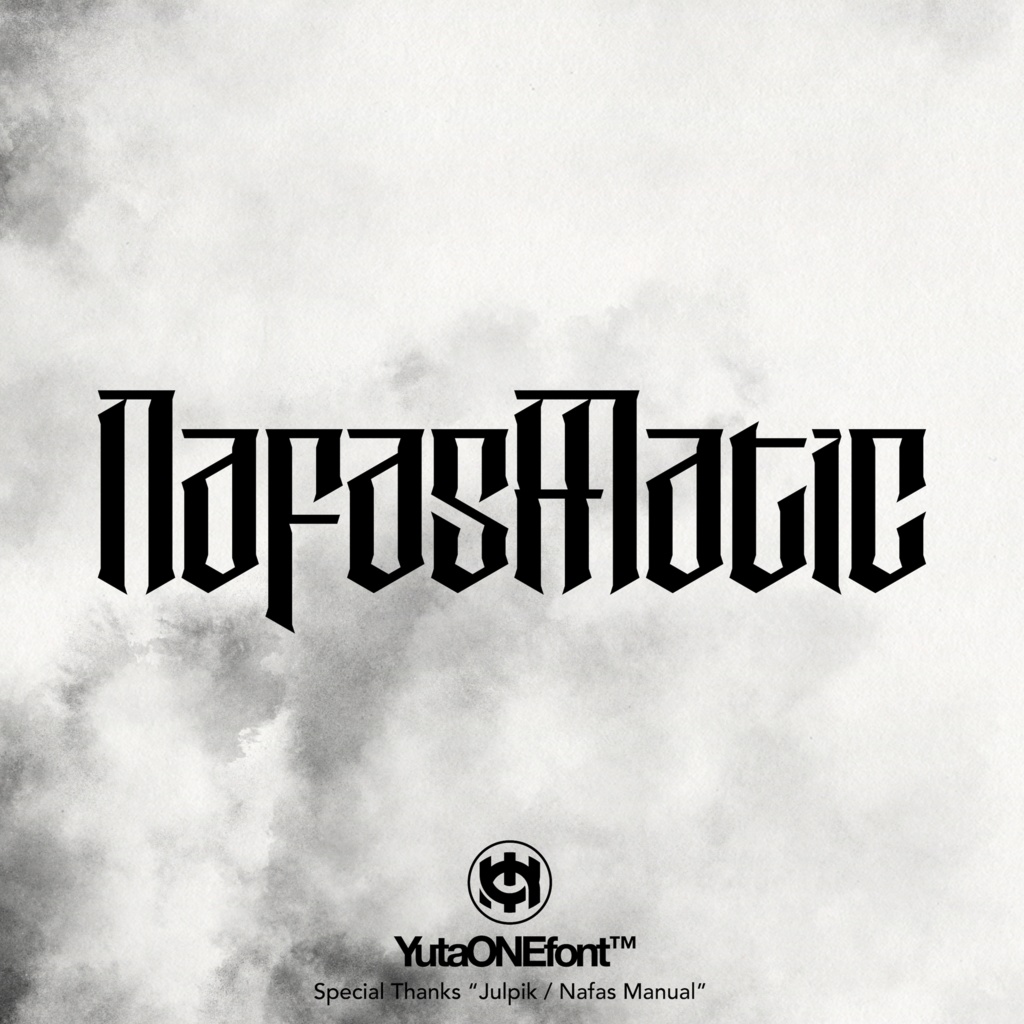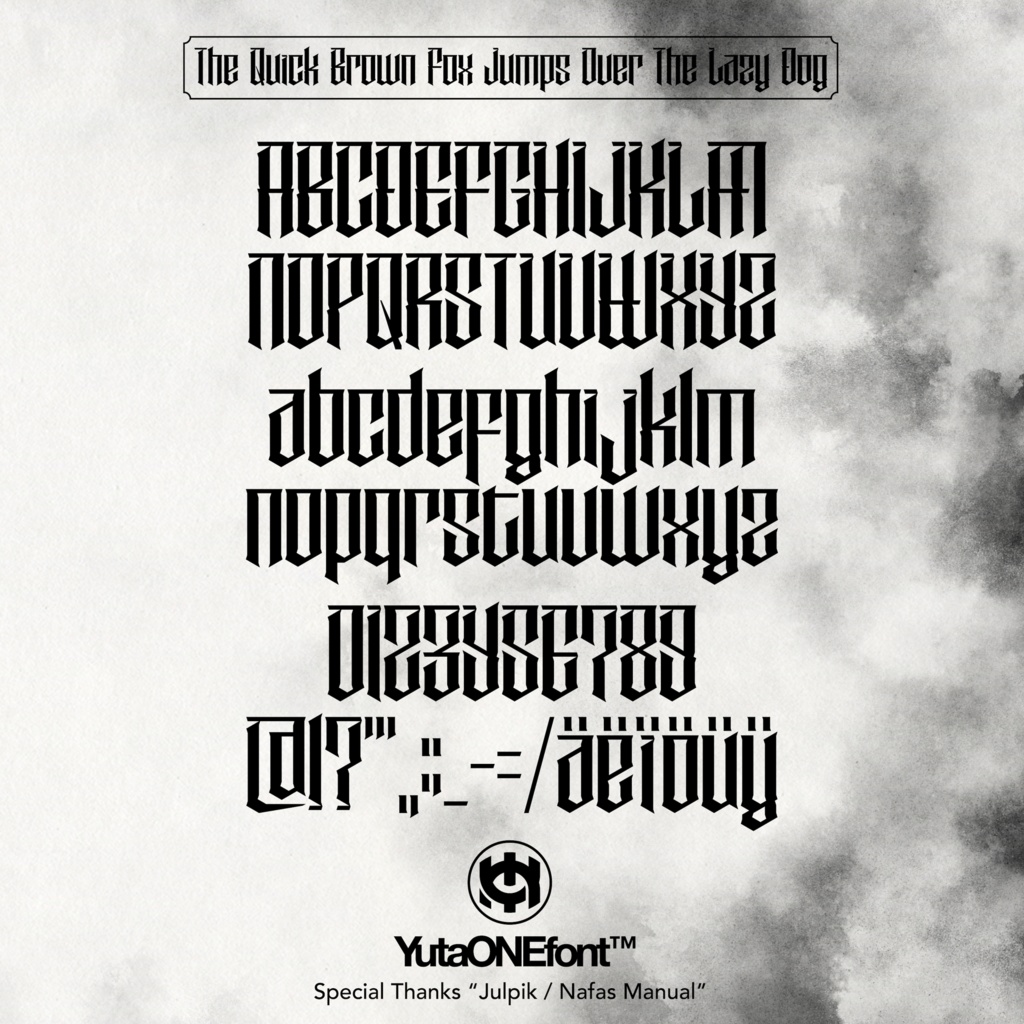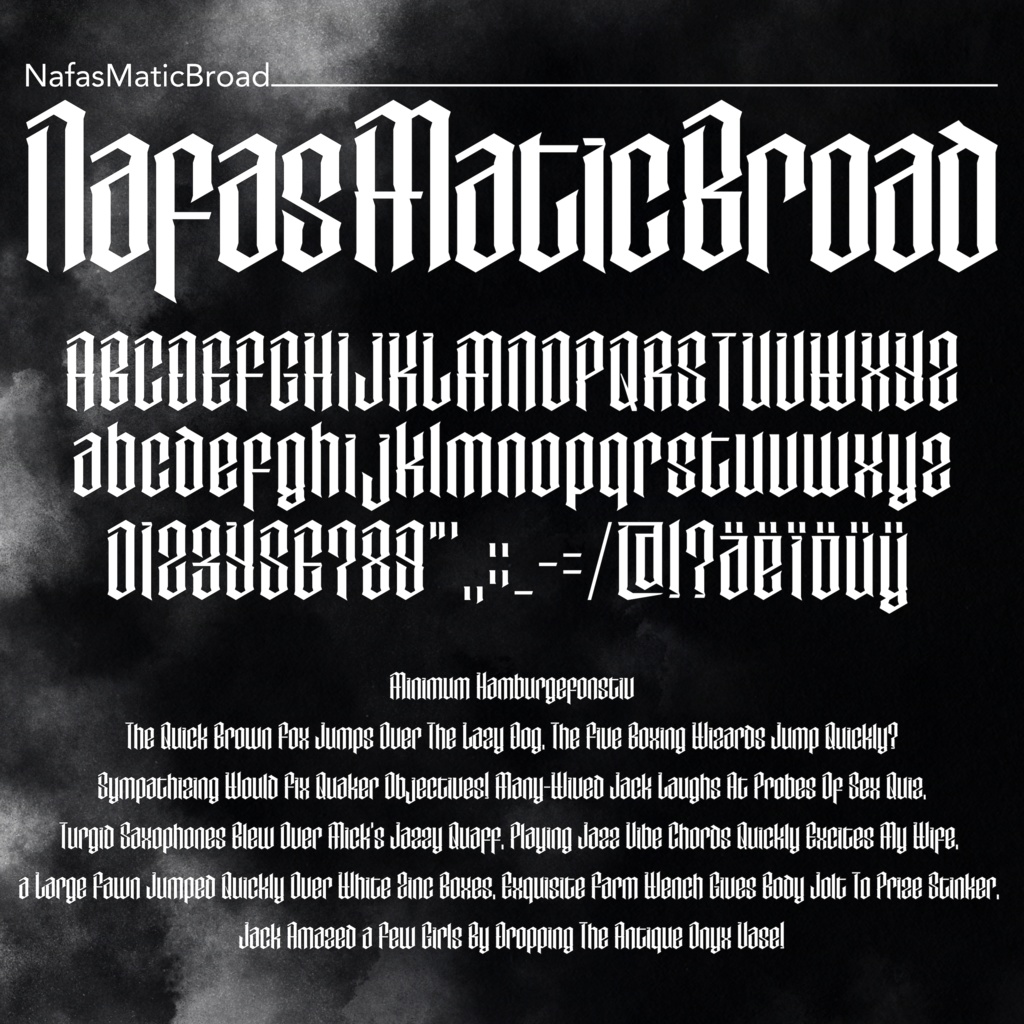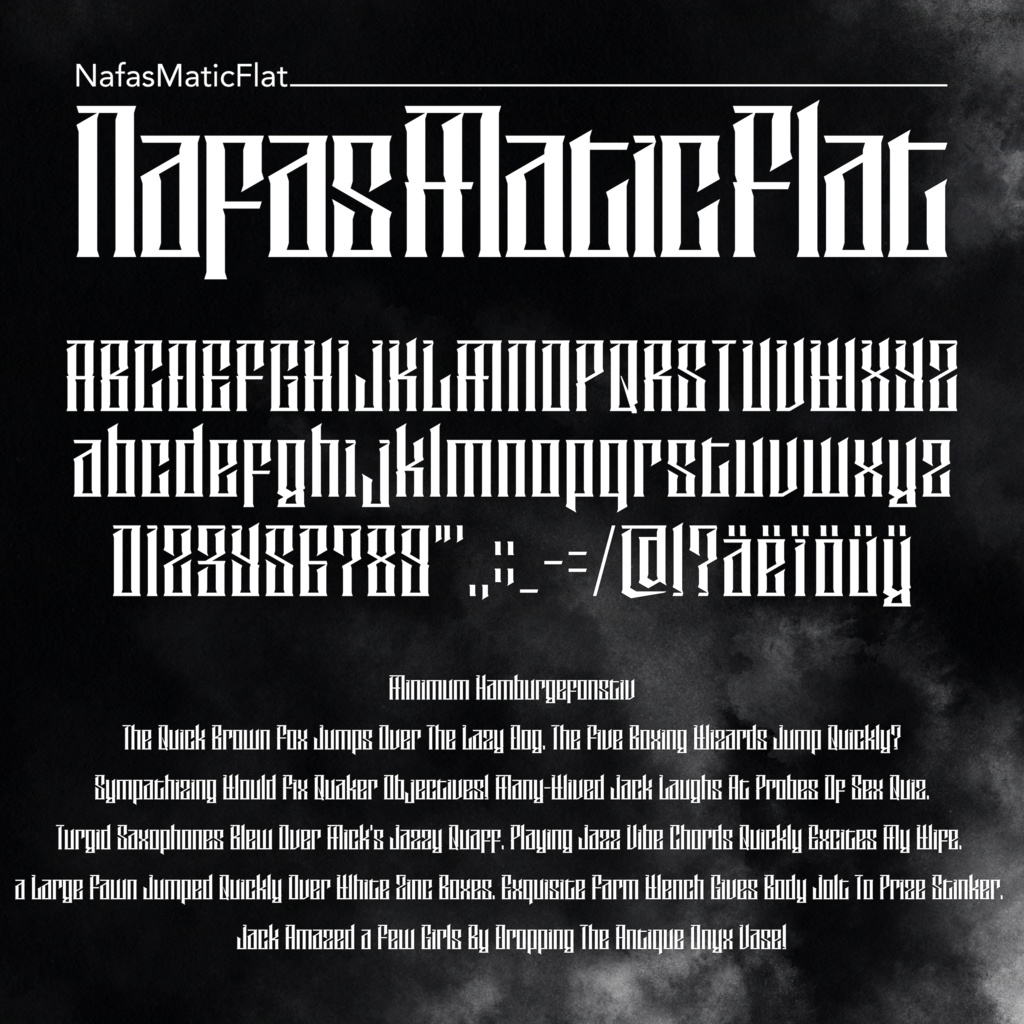
【無料】ナファスマティック|NafasMatic|ゆうたONEフォント™︎
こちらのフォントのプロトタイプを公開したところ、Nafas Manualに似ているとの報告があったので作者のJulpik氏に相談し、不要なトラブルを避けるためにJulpik氏から「Nafas Matic」という名前をもらうことにしました。 タイプフェイスは、ぱっと見が似ていても細部の微妙な違いが全体の表情を変化させるという点が非常に面白いカルチャーです。Julpik氏の「Nafas Manual」と、ゆうたONEの「「Nafas Matic」を使い比べながら、タイプフェイスクリエイティブの面白さを体験してください。 https://julpik.gumroad.com/l/NafasManual Nafas MaticはNafas Manualに敬意を示し、Nafas Manualがフリーフォントである限り有料化を行う意思はありません。 ◣◥◣ゆうたONEフォントを無料で手に入れる方法◥◣◥ ゆうたONEのフォントは、Xにて新作が発表され、目標リポスト数を突破したものが一般に配布されます。フォントは目標達成から1ヶ月間のみ無料配布され、その後有料化されますので無料のタイミングでDLしましょう。 また、フォロワー数○人突破イベントなどのタイミングで、定期的にフォントの一括ダウンロードボタンが無料開放されます。Xをフォローして応援すると共に最新情報を見逃さないようにしましょう! https://x.com/yuta_ptv ちなみに、1フォントあたり500円換算にてお得にDLできる一括DLボタンはこちらにあります。お急ぎの場合は、ぜひご検討ください。 https://yutaone.booth.pm/items/2890872 ◣◥◣ゆうたONEフォントの利用規約について◥◣◥ ゆうたONEフォントを購入する前に、以下のページを必ずご確認ください。 ーーーーーーーーーー https://docs.google.com/document/d/1jzKjcBY7Kni8GaGqFhJaeS2VThokrYWUysKsHnFCxhQ/edit?usp=drive_link ーーーーーーーーーー ※ゆうたONEが必要と判断した場合には、あらかじめ通知することなく、いつでもゆうたONEフォントの利用規約を変更することができるものとします。 ◣◥◣商品に関する注意事項◥◣◥ MacOSとAdobeソフトの組み合わせ以外での実機テストはしておりません。あくまで当フォントは「実用品の販売」ではなく「ゆうたONEの制作物に金銭的な価値をつけて応援ができる商品」です。動作の不具合については基本的に対応できませんのでご理解いただいた上でご購入ください。 ギンプやインクスペース等のグラフィックソフトだと、フォントファミリーが分割されず1つのフォントだと認識されてしまい、グラフィックソフト内のフォントブックに表示されないトラブルが確認されています。お手数ですが使用したいフォントのみをインストールする、もしくはフォント名称をそれぞれ別名に書き換えてインストールしていただきますようお願いします。(いずれソフト側が対応してくれるものと思います)